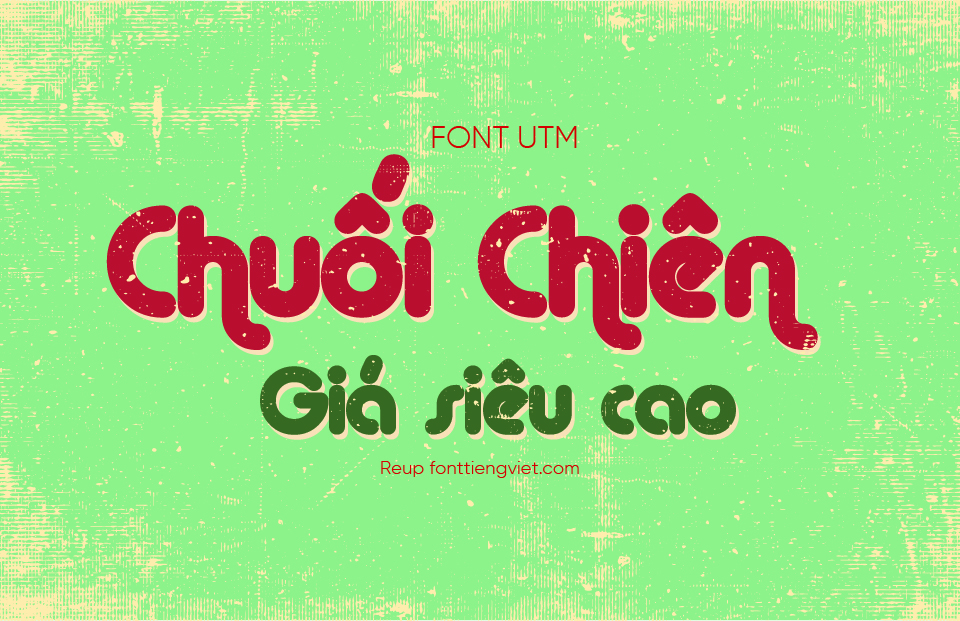
Giới thiệu về Font việt hóa UTM Alba Matter
Trong thế giới thiết kế đồ họa dành cho giáo dục và học đường, việc lựa chọn một Font Chữ phù hợp đóng vai trò cực kỳ quan trọng để tạo nên sự thu hút. Font việt hóa UTM Alba Matter là một trong những bộ font thuộc dòng trang trí nổi bật nhất. Với những đường nét dày dặn, bo tròn mềm mại và mang hơi hướng Retro, bộ font này đã được cộng đồng thiết kế tại Việt Nam yêu thích và ứng dụng rộng rãi. Phiên bản UTM Alba Matter đã được việt hóa hoàn chỉnh giúp người dùng dễ dàng gõ tiếng Việt có dấu mà không lo lỗi hiển thị, rất phù hợp cho các bạn học sinh và giáo viên khi làm báo tường hay slide bài giảng.
Đặc điểm nổi bật của Font việt hóa UTM Alba Matter
Ưu điểm lớn nhất của Font việt hóa UTM Alba Matter chính là tính nghệ thuật cao và sự vui nhộn trong từng con chữ. Bộ font này sở hữu các nét đậm nhạt đan xen tinh tế, tạo cảm giác thân thiện và gần gũi. Đối với các dự án thiết kế cho trẻ em hoặc các hoạt động ngoại khóa tại trường học, đây là lựa chọn số một. Ngoài ra, tính tương thích của font trên các phần mềm phổ biến như Photoshop, Canva hay PowerPoint cũng rất ấn tượng.
Cách ứng dụng Font việt hóa UTM Alba Matter hiệu quả
Để tận dụng tối đa vẻ đẹp của font chữ này, bạn nên kết hợp với những gam màu tươi sáng. Bạn có thể sử dụng nó cho các tiêu đề lớn, poster sự kiện hoặc bìa sổ tay học tập. Lưu ý không nên dùng font này cho các đoạn văn bản dài vì đặc thù nét chữ nghệ thuật có thể gây khó đọc nếu kích thước quá nhỏ. Hãy thử biến tấu với các hiệu ứng đổ bóng hoặc gradient để làm nổi bật hơn phong cách cá tính của bộ font này.
Kết luận và tải Font việt hóa UTM Alba Matter